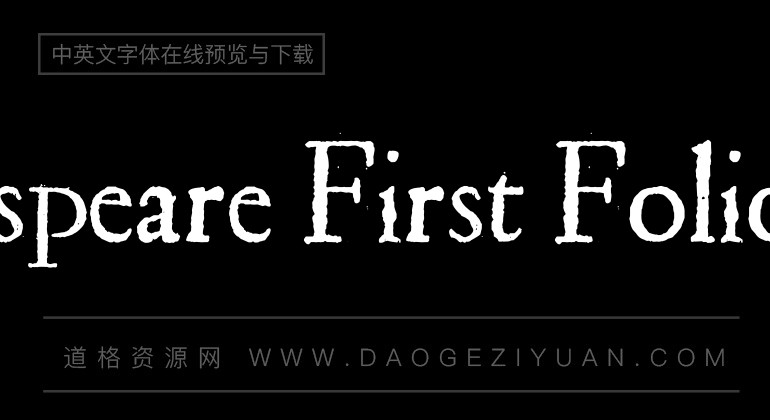
Shakespeare First Folio Font 是一款由英国著名剧作家威廉·莎士比亚的第一本法洛集编辑而成的字体。它是一种经典的文艺复兴时期的字体,也是英国印刷史上最重要的书籍之一,被誉为“英语文学的起点”。该字体以莎士比亚的第一本法洛集为基础,重新设计并制作了现代版本的字体,以更好地支持现代的文本文件。该字体具有古典的外观,但也具有现代的清晰度和可读性,适合用于打印书籍、杂志、网页和其他文本文件。内容介绍
Shakespeare First Folio Font是一款非常不错的手写艺术字体,具有很好的视觉感,适合于文化类的宣传设计、商业类品牌的广告和产品包装设计以及个性化文字排版等较多场景。